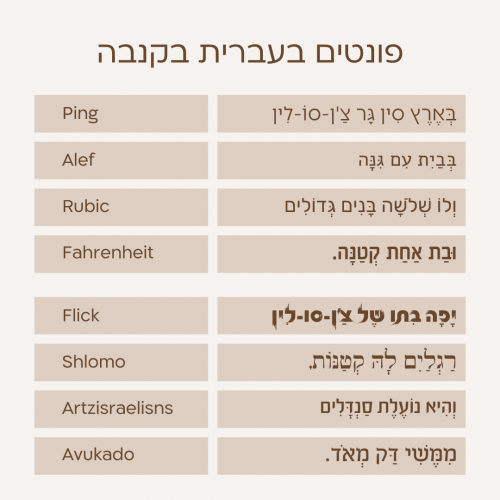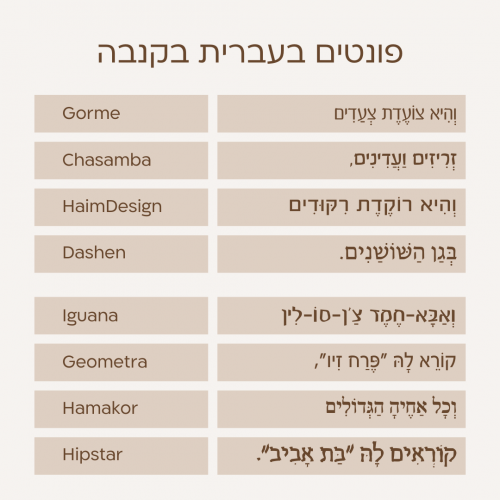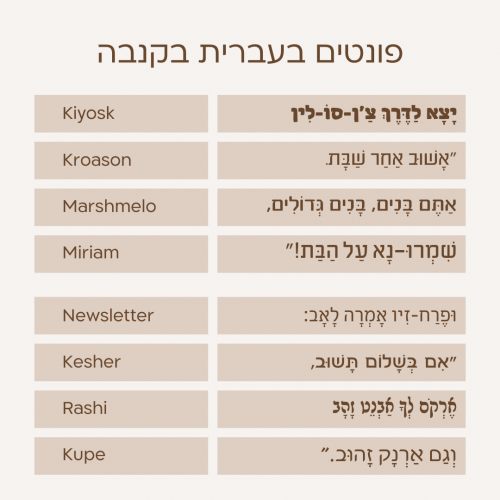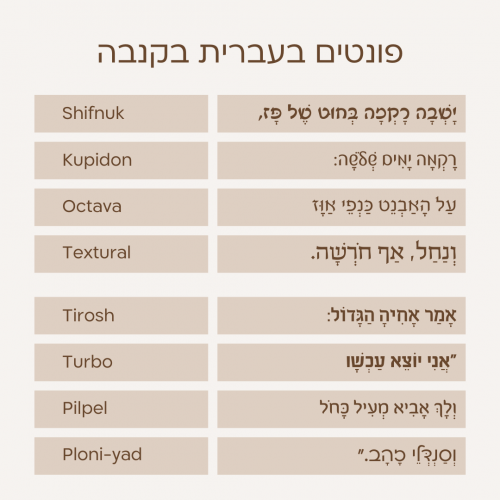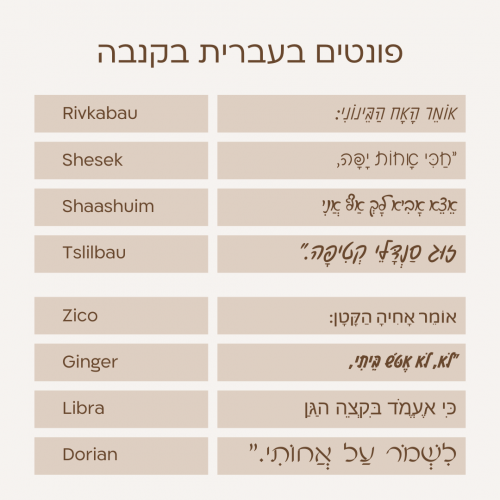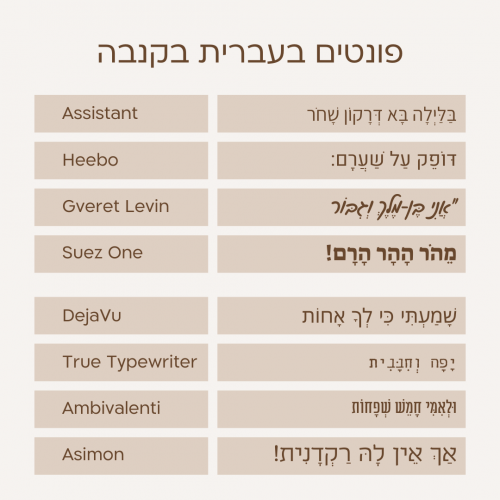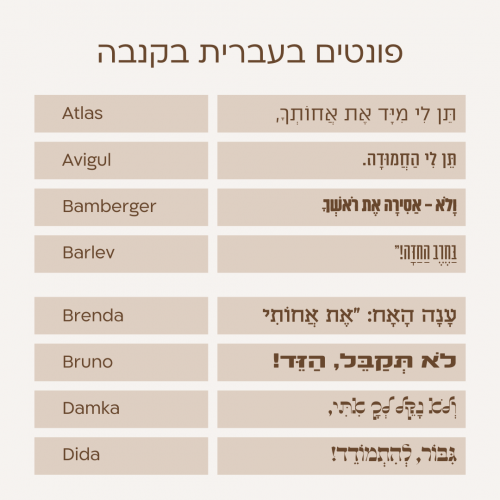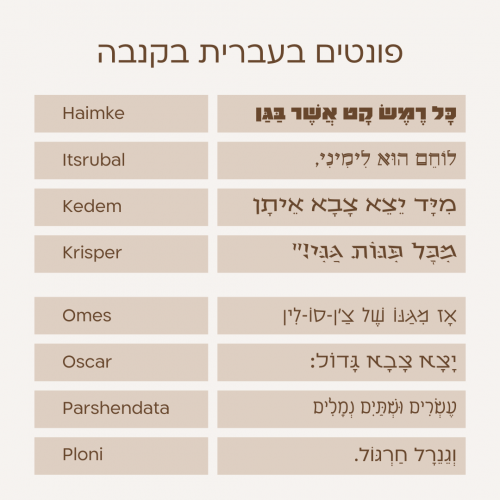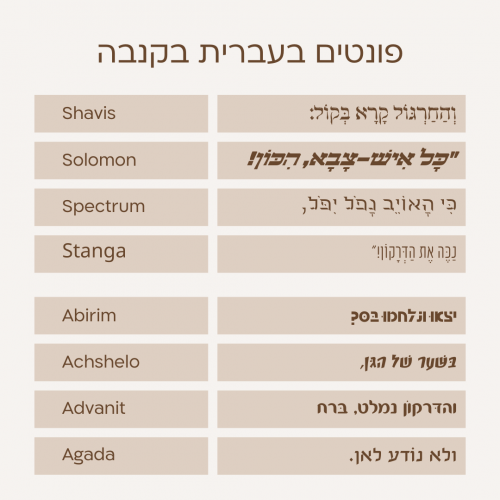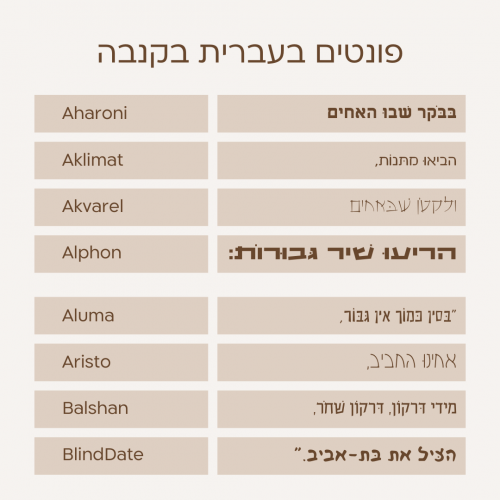
בכל מקרה, אחד האתגרים הגדולים זה הקטע של פונטים בעברית. כשזה מגיע לעברית – המערכת פשוט לא מספיק ידידותית, וקשה למצוא ולזהות את הפונטים הכי יפים והכי מוצלחים.
ובכן! הבעיה הזו מסתיימת היום. הנה, השקעתי וטרחתי והכנתי פוסט שכולו קודש לרשימה של פונטים בעברית בקנבה, כולל המחשה וויזואלית.
עכשיו, אין ספק שיש ברשימה שלהלן מספיק פונטים! ובכל זאת, למרבה הפלא, זה אפילו לא כל הפונטים העבריים שיש בקנבה. שמתי כאן רק פונטים חינמיים, ועצרתי אחרי שנגמרו השורות בשיר… כי יש גבול לכל טירוף.
אז קדימה – אתם מוזמנים לגלות את הפונטים הכי יפים והכי טובים והכי שווים בקנבה… ממש כאן למטה. אבל לפני שנצא לדרך, בואו נבהיר שאת השיר/סיפור המעולה על צ’ן סו לין כתבה הגברת לאה גולדברג (המלכה).
האם יש כתב גרפיטי בעברית בקנבה?
אני כותבת לך כאן כמה שאולי יכולים לעבור כגרפיטי:
asphalt
tip
pancher
zaam
Hal MF
אה… גם Habibi נראה טוב